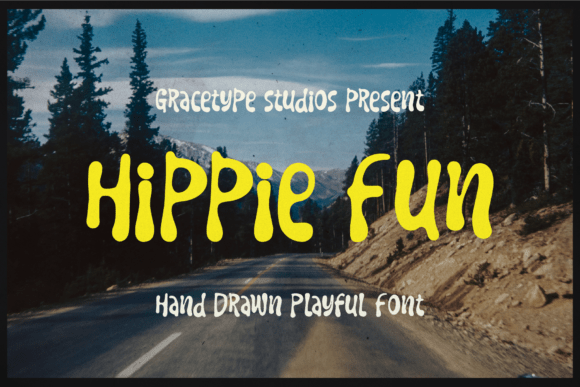
Hippie Fun
適切なデザイン要素を見つけるのは難しい場合がありますが、Hippie Funは作品を即座に引き立てる優れたコレクションを提供します。
POD(オンデマンド印刷)製品、結婚式の招待状、またはソーシャルメディアのグラフィックを作成している場合でも、Hippie Funは理想的です。